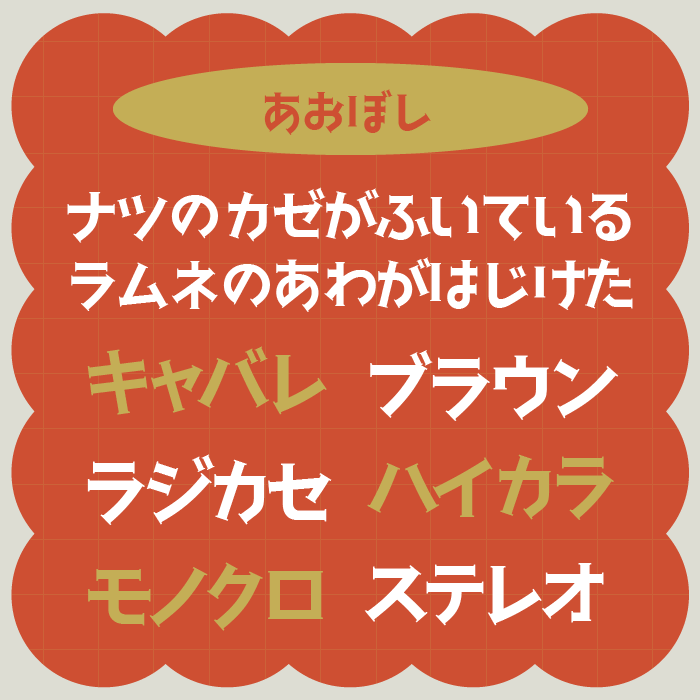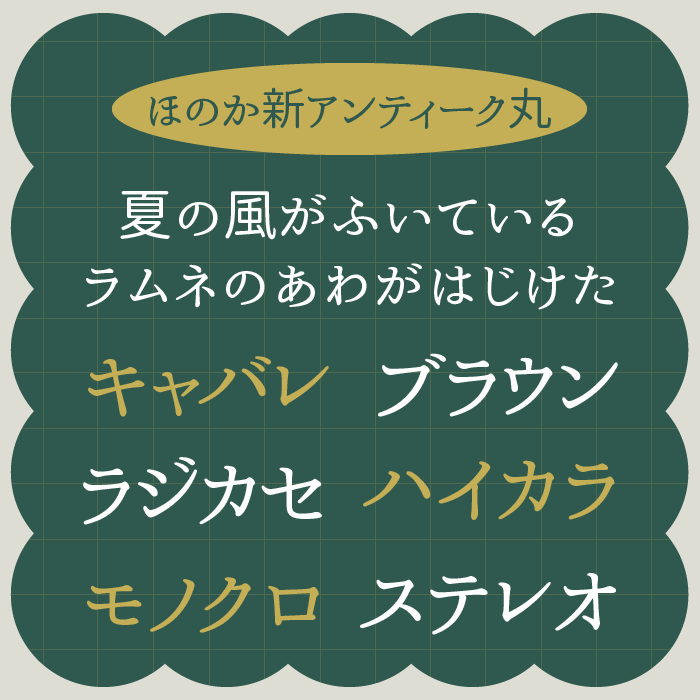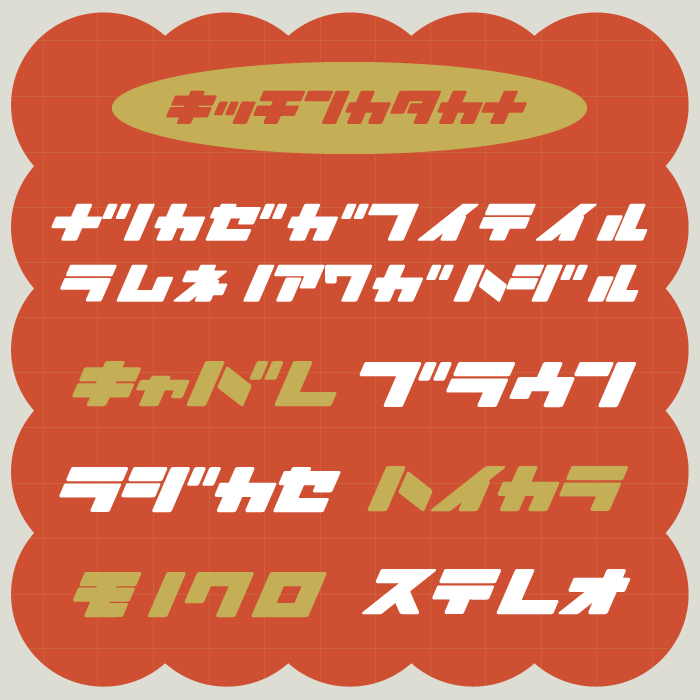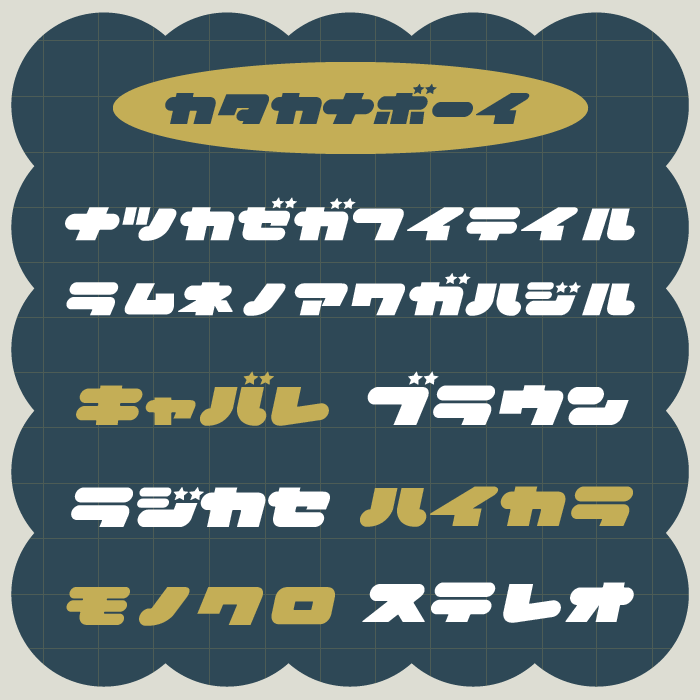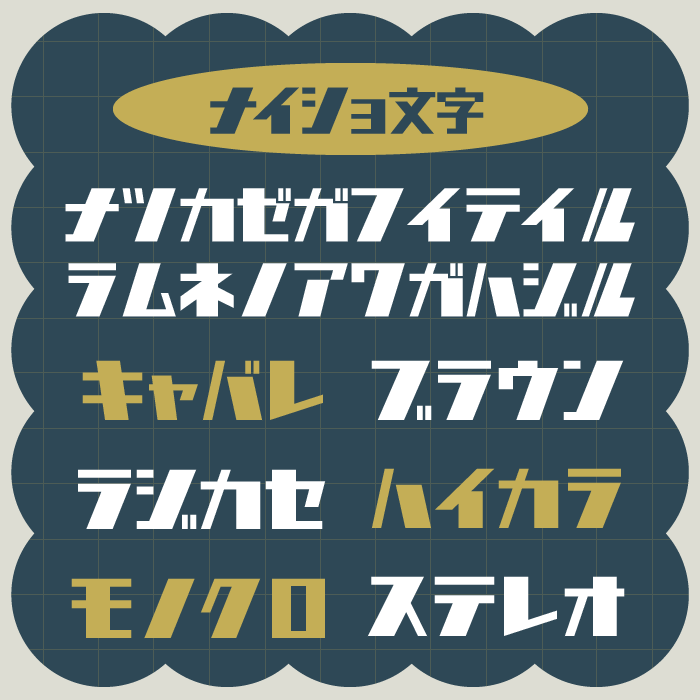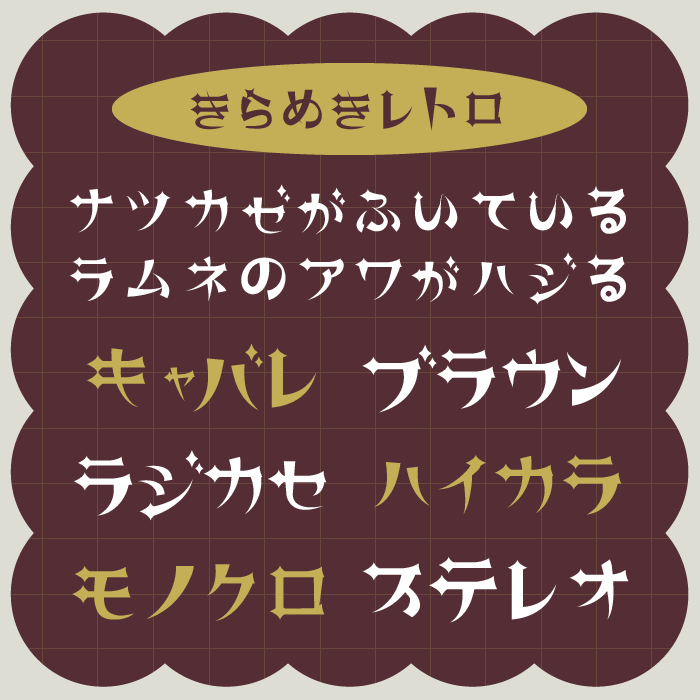
今回は、ノスタルジックでありながら、今っぽく“映える”オシャレでレトロな日本語フリーフォントをご紹介します。
昭和の看板や雑誌広告を思わせるタイポグラフィ、クラシカルな丸みや味のあるかすれなどそんなレトロな魅力に、現代の洗練されたセンスをかけあわせたデザインは、どこか懐かしくも新鮮を感じるフォントばかりです。
今回は、カフェのロゴや古着系ショップのPOP、ZINEやレトロ雑貨のパッケージにもぴったりな、日本語のフリーフォントをピックアップしました。オシャレでちょっぴりノスタルジーな雰囲気を演出したいときに、ぜひ参考にしてみてください。
オシャレでレトロな日本語フリーフォントのまとめ
以下のサンプル画像は、本記事で紹介しているフォントの一部ですが、文字だけで、懐かしさを感じさせてくれるレトロでオシャレなフォントです。
以下よりオシャレでレトロな日本語フリーフォントの紹介になります。
ビルの谷間と高架下フォントは、漢字とひらがな、カタカナのでこぼこ感が可愛いらしいデザインフォントです。
統一しすぎない字形のデザインがポップでレトロで懐かしい印象を作り出しているフォントです。あえて漢字とひらがな・カタカナのサイズ感を変えていることも素敵です。
きなりゴシック
きなりゴシックフォントは、華奢で有機的なシルエットとても美しく、繊細で優しい雰囲気を表現したい際に活用できるフォント。モダンさも感じつつもどこかアンニュイなレトロな雰囲気を感じることができるフォントです。
うつくし明朝体
うつくし明朝体フォントは、はねやはらいに柔らかさ、流れるような線の使い方が美しいです。レトロな味わいを感じる漢字とかなのバランスなど求められるオールドスタイル明朝体のエッセンスは残しつつ、モダンに感じされる素敵なフォントです。
ほのか新アンティーク丸
ほのか新アンティーク丸は、漢字が丸ゴシックとかな文字が明朝体が組み合わせれていることで、少しレトロな印象も感じるフォントとなっています。
作者様いわく「かしこまった雰囲気や懐かしさ・寂しさ・哀愁を演出したい場面で使用すると、効果的なフォントです。」とのことです。エモーショナルな哀愁漂う雰囲気とぴったりです!
シャープ旧ロゴ
シャープ旧ロゴは、家電メーカー「シャープ」の昔のロゴをベースに製作されたフォント。日本の昭和レトロな香りがたっぷりなユニークフォントになっています。
ロゴやタイトルに向いています。
新レトロ丸ゴシック
新レトロ丸ゴシックは、写植時代に使われていた丸ゴシックを参考に作られた懐かしい表情のあるフォント。丸ゴシックで柔らかい印象だけど、かな文字が少し変わったレトロ感あるフォントですね。
作者様いわく「懐が狭めで表情のある柔らかな仮名は、昭和~平成の印刷物やテレビのテロップ雰囲気を出すのに似合うはずです。」とのことです。
姫明朝しらゆき
姫明朝しらゆきminiフォントは、白雪姫の物語をイメージした明朝体フォント。
ひらがなは「白雪姫」、カタカナは「7人のドワーフ」、漢字は「王子様」のイメージで、丸みを帯びたシンプルなラインに、文字にストーリー性や物語を感じられる素敵なフォントです。
はちまるポップ
はちまるポップ(Hachi Maru Pop)フォントは、80〜90年代にかけて流行した丸文字にインスパイアされ製作さ、モダンにアレンジされた丸文字系フォント。
昔の少女向けマンガなどにこのような文字が使われているのをよく見かけましたね。丸みがポップな印象がありとっても可愛らしい文字になっています。現代風にアレンジされていますが、きちんと昔の印象も残したままなので、レトロな印象もあります。
全員集合!ポップ体
全員集合!ポップ体フォントは、80年代のテレビ番組で使用された雰囲気を出した手書き文字フォント。
手書き文字フォントとしてもかわいい仕上がりですが、80年代のバラエティ番組を彷彿させる、どこか懐かしいレトロな趣がある手書きになっています。少しエモくて素敵な手書き文字です。
Oradano明朝
Oradano明朝フォントは、「活字の格好よさの源泉を考える材料」をコンセプトに、東京築地活版製造所が明治30年に販売しあるいは印刷していた書籍に基づき作られたフォント。
インクの滲みや活字ならではの滲み感がとっても渋い!
バナナスリップ
バナナスリップ(plus)は、太くて強い骨格と、微かな可愛らしさが絶妙なフォントです。堅苦しくはしたくないし、可愛すぎるのもちょっと違う、みたいなシーンのときにはピッタリなフォントです。みんな大好きバナナスリップ!
解星デコール
解星デコールフォントは、文字の先端の丸い飾りがかわいらしい装飾になっており、ユニークなフォント。喫茶店とかの看板ロゴなどに使われていそうな文字です。ステキ。
あおさぎ
あおさぎフォントは、太めの明朝体をベースとしていて、遊びココロを入れているので、明朝体ですが固くなりすぎず柔らかい印象があります。少し手書き感のような柔らかさがあり、レトロっぽい雰囲気を感じるデザインです。
ゴンタかな
FZゴンタかなフォントは、インパクトがある超超極太のひらがな・カタカナフォントになります。
ミスターグレイ
ミスターグレイフォントは、ポップな印象とレトロな印象が混じっているようなとっても素敵なフォントです。
レトロゴ
レトロゴフォントは、昔のナショナル(現Panasonic)のような電機系会社のロゴなどに私用されていた懐かしい雰囲気をもつデザインフォントです。
ロゴなどに向いているフォントかと思います。
ナイショ文字
ナイショ文字フォントも同様に某家電メーカーの旧ロゴをベースに制作されたフォント。
細い横線・太い縦線で構成されるユニークな文字は、昭和によく流行っていた字形が懐かしさを感じさせてくれるレトロなフォントになっています。
しあさって
しあさってフォントは、さまざまな太さと、色んな方向に向いているユニークなフォント。遊び心があるほど良いゆるさと、ほど良いレトロ感がステキです。ひらがな・カタカナのみのフォントです。
かりぐらスキップ
かりぐらスキップフォントは、文字がスキップをしているような軽快なハネやハライが特徴的なフォント。かわいいー!
カタカナボーイ
カタカナボーイフォントは、カタカナのみのフォントになっております。少年のような元気いっぱいの可愛らしいフォントになります。Y2Kや平成初期レトロを彷彿させる文字です。
名前のような少年が冒険にでていくような元気な印象があるフォントで、ひらがなや漢字も見てみたかったなぁ。※カタカナのみフォント
きらめきレトロ
きらめきレトロフォントは、レトロ、アンティーク風な文字単体でも使いやすいデザインを想定して制作され、ダイヤの装飾が特徴のフォント。
さまざまな太さに強弱があるストロークがとっても可愛らしいフォントになっています。
レトロランプ
レトロランプフォントは、白熱電球「トウランプ®」のロゴのレタリングにインスパイアされて作ったフォント。
昭和中期から、白熱電球が主流だった時代によくみかけた看板に使われていた文字ですね。
キッチンカタカナ
キッチンカタカナフォントは、システムキッチンのメーカー「クリ○ップ」のロゴをベースに製作されたカタカナフォント。極太で少し斜体がかかったロゴ昔流行りましたね。
収録文字は、カタカナ・数字・英字大文字が収録されています。
晩秋レトロミン
晩秋レトロミンフォントは、レトロな雰囲気と明朝体のような特徴をもっている、ユニークで少しクセの強いフォントです。
払いやはねにユニークな装飾がついていることで、どこか懐かしいレトロな趣があるフォントです。収録文字は、ひらがな・カタカナ・英数字・一部約物・漢字(教育漢字+α)となっています。
鉄路タイプフェイス
鉄路タイプフェイスフォントは、鉄道っぽくてメカっぽいカッコイイフォントです。1文字ごとにいい具合に切り込み(スリット)が入っていることで、ロゴタイトルのように作りこんである文字のようにも見えます。
ロボットアニメのタイトルや題字などに使われていそうなカッコイイフォントです。
あおぼし(Aoboshi One)
あおぼし(Aoboshi One)フォントは、太さが均一で細いセリフの特徴をもっているかなフォントです。
だるまドロップ(Darumadrop One)
だるまドロップ(Darumadrop One)フォントは、太め線の手書き文字のようなユル可愛くて、どこか懐かしいレトロモダンなフォントです。
墨でかいたような滲みが、和を感じさせるデザインになっているのも特長です。
くるん・デコ
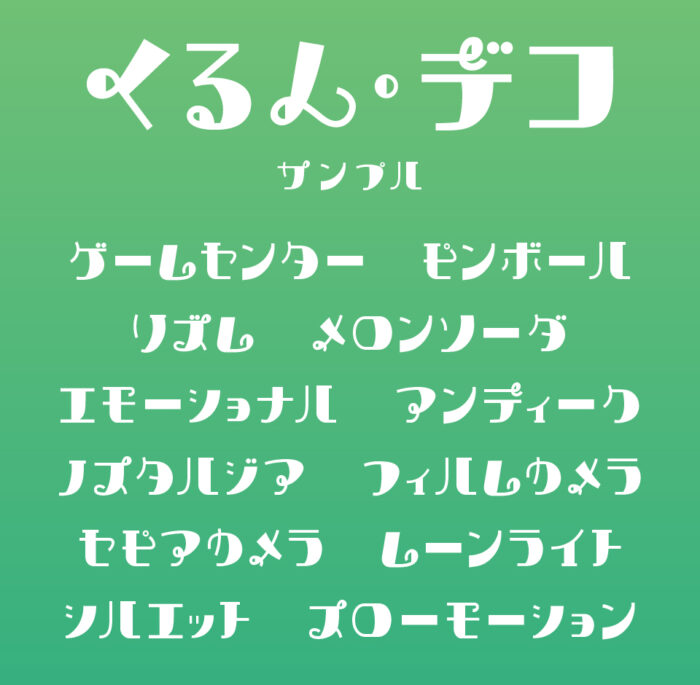
くるん・デコフォントは、線先などがくるんとした可愛い装飾となっているデザインフォントです。
カナテン
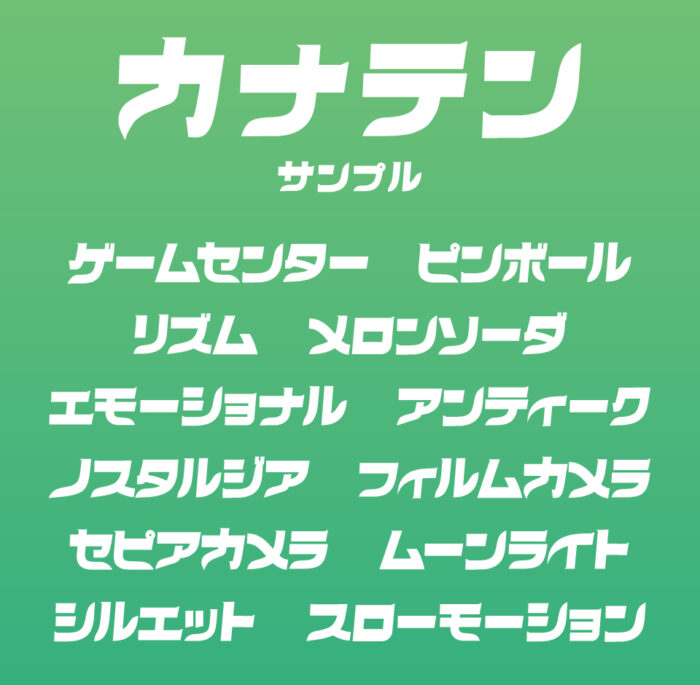
カナテンフォントは、斜体のフォルムに、シュッっとした勢いのあるデザインが特徴的のカタカナフォントです。
トレゴ
トレゴフォントは、昭和レトロの雰囲気が漂う可愛らしい「かな文字」フォントです。
欧文書体「Trajan Sans」から着想を得て作られたフォントということで、文字の先端部分の装飾が特徴的なフォントとなっています。